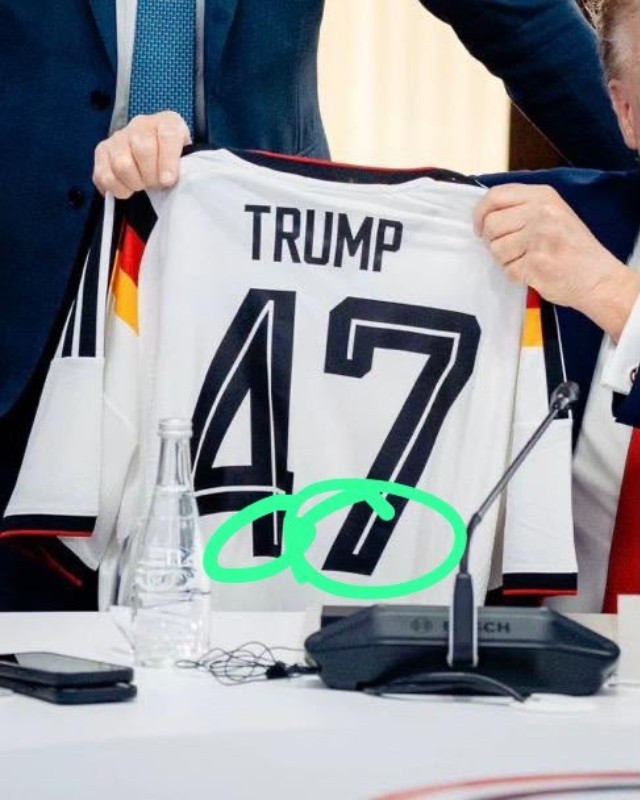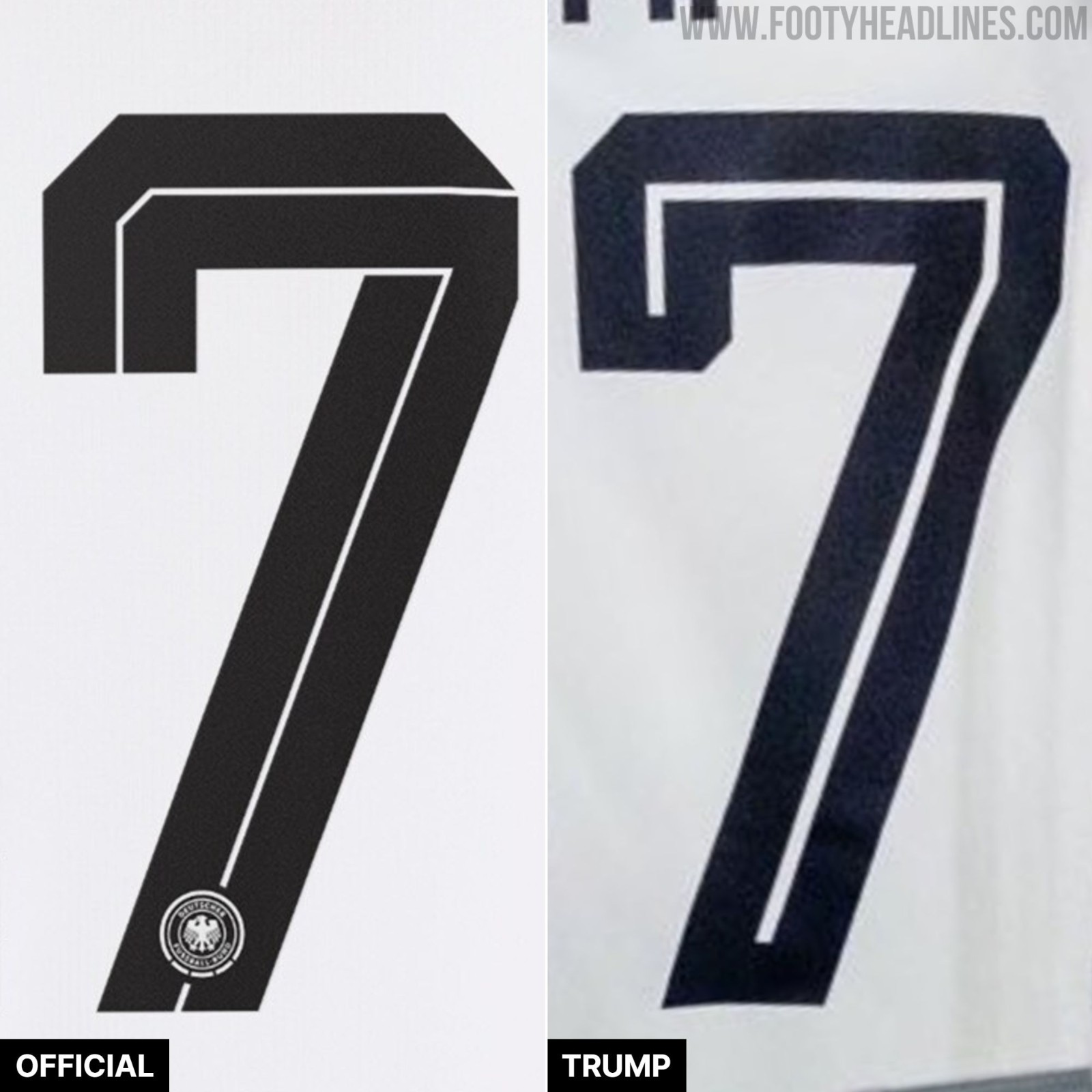
Alemania regala a Donald Trump una camiseta de Adidas para el Mundial de 2026 con una tipografía no oficial
• Regalo a Donald Trump: Alemania regaló al presidente estadounidense Donald Trump una camiseta personalizada de la selección alemana con su nombre "TRUMP" y el número 47, como obsequio tardío por su 80.º cumpleaños durante la cumbre del G7 en Francia.
• Tipografía no oficial: La camiseta entregada a Trump presentaba una tipografía incorrecta y no oficial para el nombre y el número, a diferencia de la usada por la selección nacional y sin otros elementos oficiales como el logo de la DFB en los números.
• Motivo de la discrepancia: La Cancillería alemana explicó que la tipografía no oficial se debió a una subcontratación urgente de la impresión a una tienda deportiva local, ya que la tienda oficial de Adidas en Berlín no pudo personalizar la camiseta a tiempo antes del viaje a la cumbre del G7.
Actualización - Viernes, 19 de junio de 2026: La Cancillería alemana ha aclarado la situación sobre el tema de la tipografía de la camiseta de «Trump Germany», explicando que la discrepancia se debe a la apretada agenda previa al viaje. Según informan los medios locales, la tienda oficial de Adidas en Berlín no pudo plasmar a tiempo el nombre y el número auténticos antes de que el político Friedrich Merz partiera hacia la cumbre del G7 en Francia. Por eso, el trabajo de impresión urgente se subcontrató a otra tienda deportiva local para garantizar que el regalo estuviera listo.
Según se informa, esta tienda externa aseguró a la Cancillería que podía proporcionar una réplica idéntica de la tipografía oficial de la selección alemana, pero el resultado final de la camiseta muestra claramente un tipo de letra estándar y no oficial.
El canciller alemán Friedrich Merz le regaló al presidente de EE. UU., Donald Trump, una camiseta personalizada de la selección alemana durante la cumbre del G7 en Francia. Entregada como regalo tardío por su 80.º cumpleaños, la camiseta lleva el nombre «TRUMP» y el número 47 en la espalda, en referencia a que Trump es el 47.º presidente de Estados Unidos.
La camiseta de Alemania de Trump tiene una tipografía «no oficial»
Sin embargo, si te fijas bien en la camiseta, verás varias imprecisiones evidentes. Las letras y los números usan una tipografía incorrecta que no coincide con la tipografía oficial de Adidas que usa la selección nacional. El logotipo de la DFB brilla por su ausencia en la parte inferior de los números, y el número más pequeño de la parte delantera ni siquiera aparece.
Es probable que estas discrepancias se deban a las restricciones actuales de venta al por menor. La tienda online oficial de Adidas no permite nombres ni números personalizados a tu antojo, sino que solo ofrece selecciones oficiales de jugadores preestablecidas. Por otro lado, se dice que los nombres y números personalizados a través de la tienda de la DFB y 11Teamsports vienen con esta tipografía no oficial.